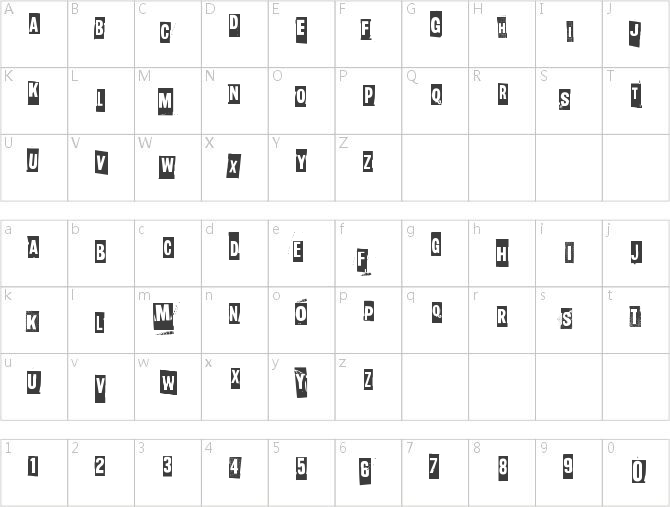
字體名稱: Slave o
Slave only dreams to be king
Slave only dreams to be king字體字庫是一款讓人賞心悅目、百看不厭的英文字體,適合各類廣告和產品包裝設計應用,字體大小0.08MB,格式為ttf字體,上傳用戶是惠祥博達,作者/版權方為未知